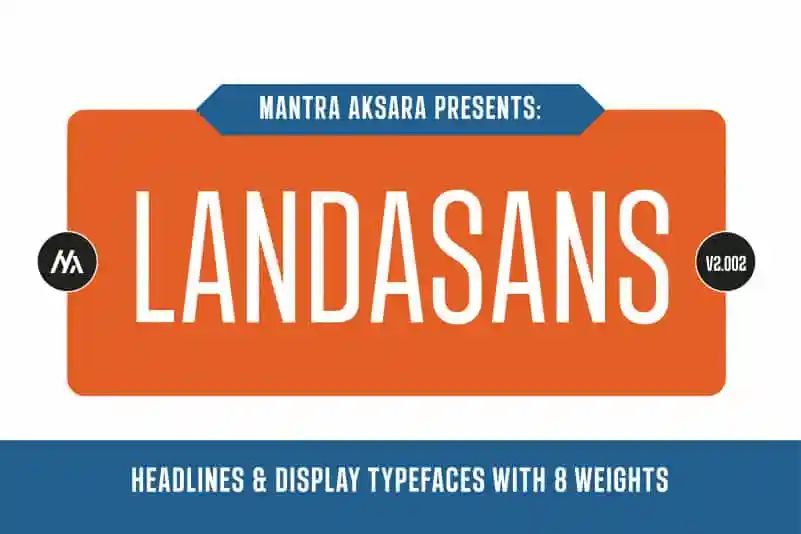
Landasans Sans Serif Font – Download Grátis
A Landasans Sans Serif Font é uma elegante tipografia sem serif que se destaca pela simplicidade e geometria pura. Baseada em formas geométricas, essa fonte tem um design concentrado e simples, projetada para atender a múltiplos projetos de projeto. Ideal tanto para uso comercial quanto para editoriais, ela é perfeita para criar elementos de marca, logotipos, embalagens, títulos e headlines. Seja para revistas ou anúncios, essa fonte combina sofisticação com simplicidade, tornando-a uma escolha versátil e funcional. Para saber mais sobre a Landasans Font e seu uso comercial, visite os links fornecidos. Este projeto de tipografia é um ótimo exemplo do que a CreativeMarket e YouWorkForThem oferecem em qualidade e recursos para designers gráficos.
Designer: mantra aksara